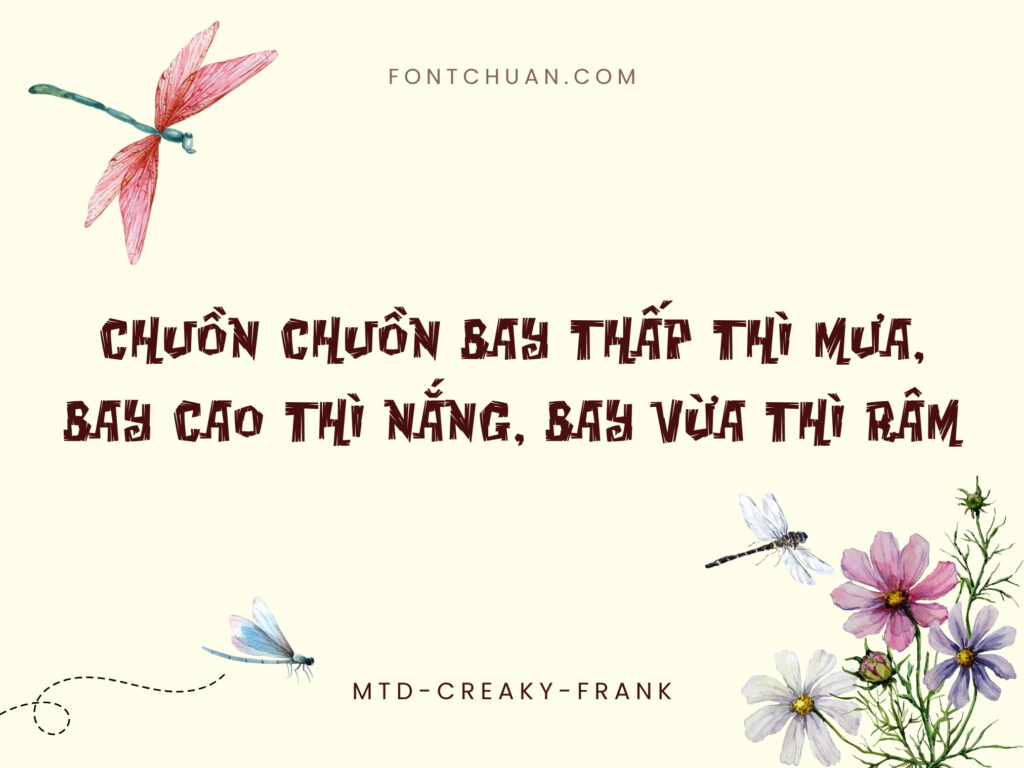
Font MTD Creaky Frank là một kiểu chữ trang trí mang phong cách cổ điển, được thiết kế bởi Font Diner và đã được Việt hóa bởi Mộc Hạ. Font này hỗ trợ đầy đủ tiếng Việt cùng hơn 90 ngôn ngữ khác, mở rộng khả năng ứng dụng trong các thiết kế đa ngôn ngữ. Đây là một trong những phông chữ được cộng đồng thiết kế đánh giá cao và sử dụng trong nhiều dự án sáng tạo, đáp ứng nhu cầu đa dạng của người dùng.
MTD Creaky Frank nổi bật với các đường nét độc đáo và phong cách cổ điển, tạo cảm giác hoài niệm và ấn tượng. Font rất phù hợp cho các thiết kế logo, tiêu đề, bao bì sản phẩm, thiệp mời và các ấn phẩm đòi hỏi sự khác biệt và nổi bật. Các ngành nghề phù hợp bao gồm quảng cáo, giáo dục, công nghệ, thiệp cưới và ảnh cưới. Font này cũng lý tưởng cho các sự kiện như Tết, Giáng sinh, Valentine và các lễ hội khác.